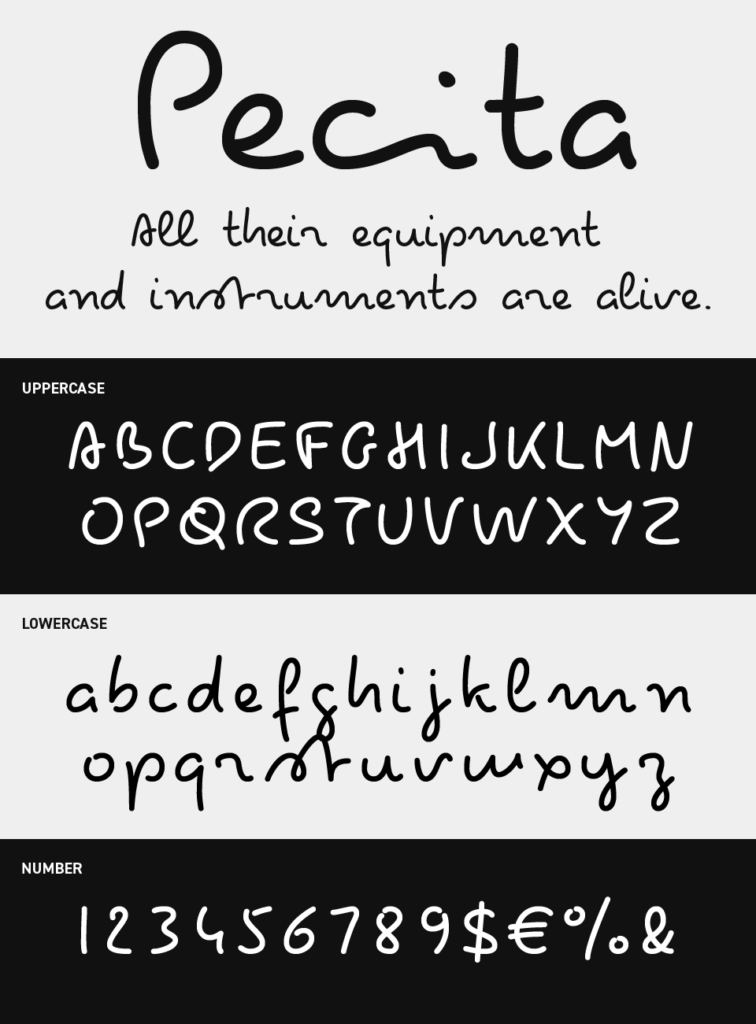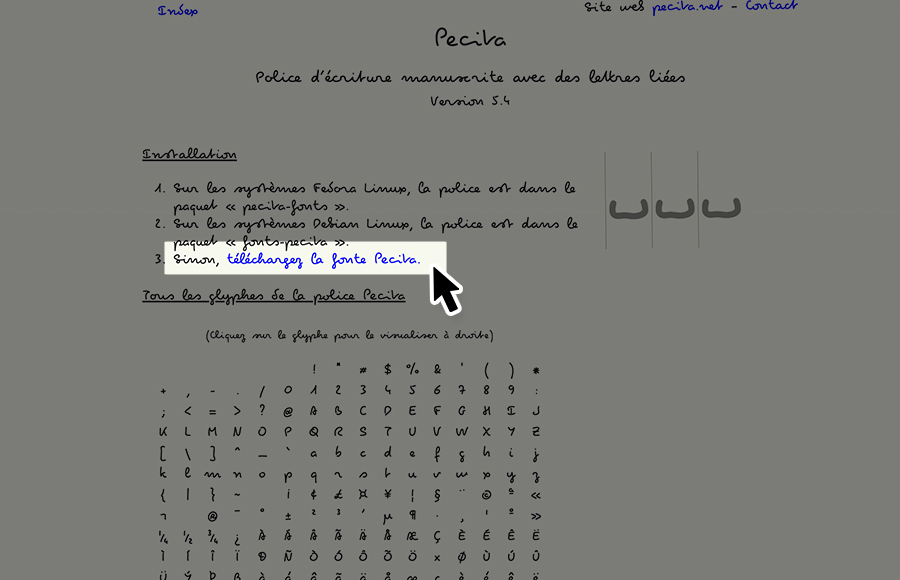
Pecitaフォントは、手書きのゆらぎと丸みが感じられる、親しみやすく柔らかな空気感を持った手書き風フォントです。
少し読みにくさもありつつもリアルなラフ感とラフすぎない整い方があり、日記のような温度感やカフェのメニュー、SNSのビジュアルにもなじみやすいフォントです。
軽やかな線の流れがリズムを生み、カジュアルなタイトルやコピーに自然なあたたかみを添えるフォントです。